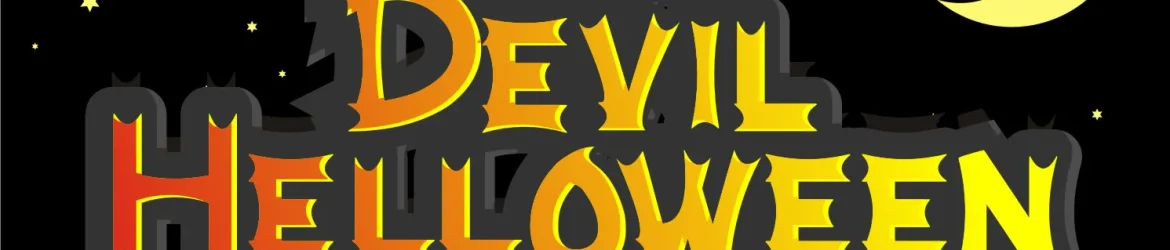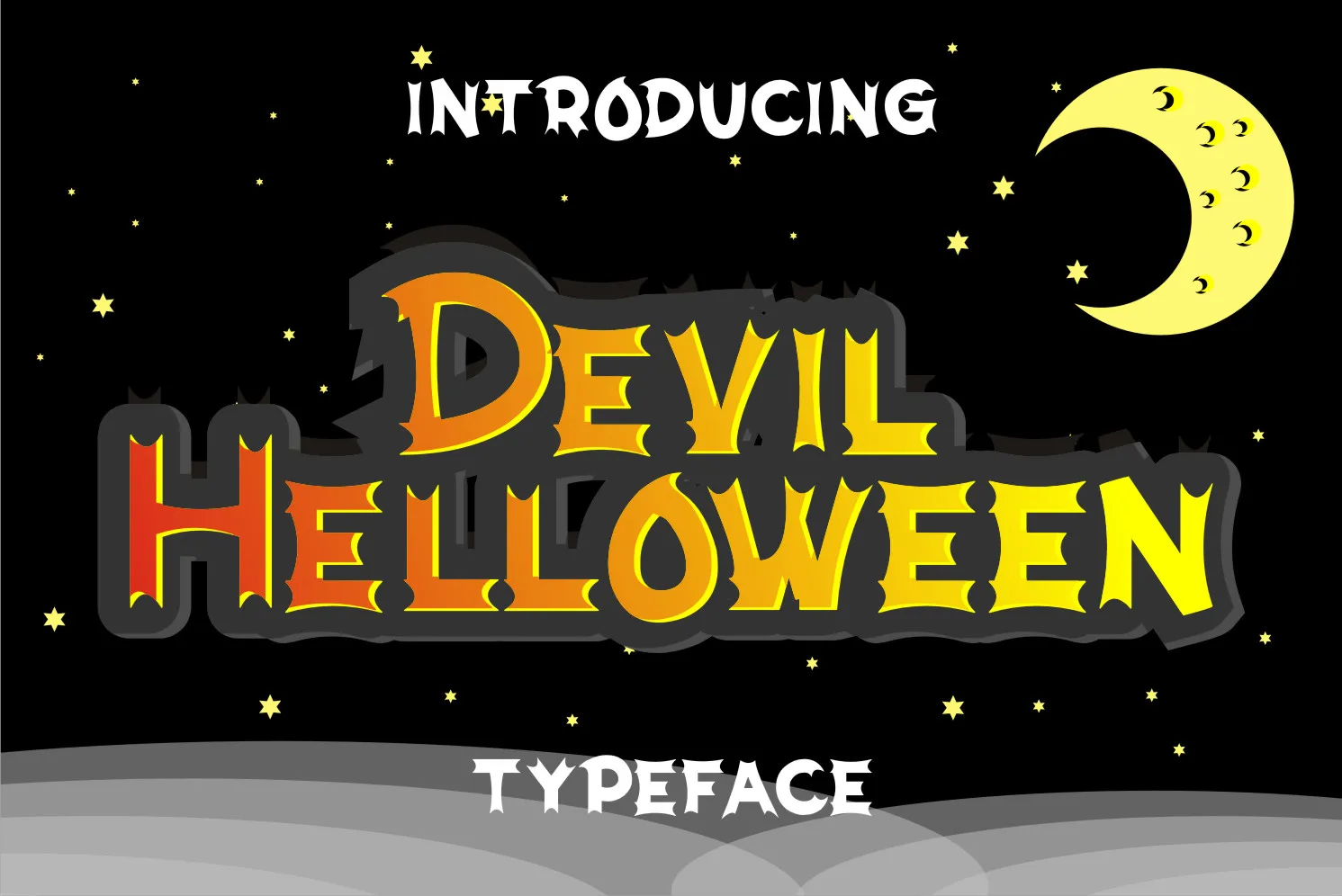
Devil Helloween Font
Aqui está uma descrição para a página de download da fonte ‘Devil Helloween Font’ na categoria Display Fonts: Se você está procurando por algo que brinque com as cores escuras e temidas, você encontrou seu elemento perfeito! A fonte ‘Devil Helloween Font’ é uma escolha incrível para projetos decorativos relacionados à festa de Halloween. Ela se destaca com letras grossas e um ar sobrenatural que invita a criatividade nas mais variadas ideias de decoração ou arte. Esta fonte, criada pela letterfiastudio, é perfeitamente adequada para qualquer projeto halloweeniano. Ela promete transformar mensagens e design em algo realmente assustadoramente bonito. O limite está apenas no seu próprio imaginário! Seja uma estilosa tag de produto, um flyer de festa ou até mesmo o tema de sua próxima arte digital – a ‘Devil Helloween Font’ tem tudo que você precisa para dar vida à sua ideia.